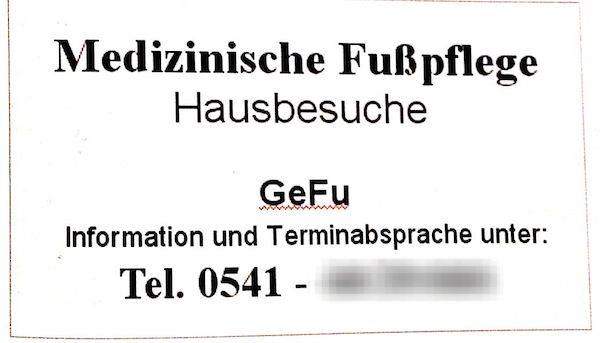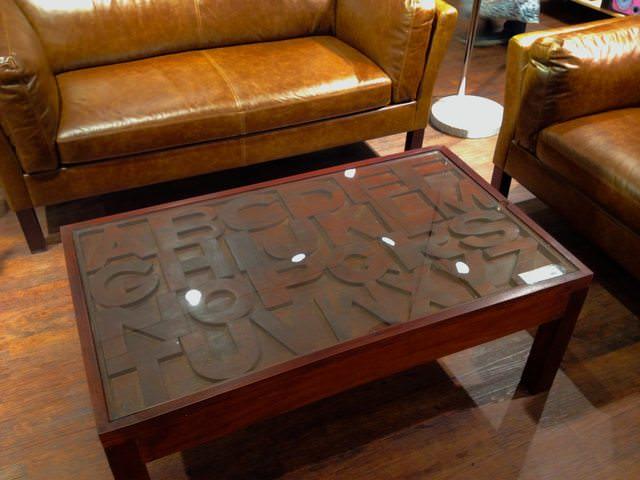
Die Leerzeichen können dann ja die Frauen beisteuern …
Hm. Ich kenne die eine oder andere Frau, die durchaus einen Gedankenstrich beisteuern könnte. :-|
Leerzeichen auch nicht … eher Lehrzeichen  :biglove: .
Ich spendiere eine Locke.  ;-)
Dann kriegen wir zumindest eine Mail-Adresse zusammen ...
Falls noch jemand was für’s Wohnzimmer braucht:
gesehen bei Butlers in Osnabrück
Ist das Bild spiegelverkehrt?  :-|
Das Foto ist nicht gespiegelt. Gespiegelte Buchstaben sehe ich jetzt auch keine, ich finde aber besonders M und W merkwürdig mager ...
War auch nicht ganz ernst gemeint :-) Ich sehe vermeintlich alte Holzlettern, die spiegelverkehrt sein müssten, damit sie im Druck seitenrichtig sind. Und das W sieht mir aus wie ein M, das auf dem Kopf steht.
Export durch Bildschrimfoto inklusive Rechtschreibkorrektur :hammer:
Aus unserem Gemeindeblatt und die Anzeige ist da so nicht das erste Mal drin  :neenee:  (Die Telefonnummer habe ich unkenntlich gemacht …)
Ja, gab ers nicht mal früher solche Massage-Sandalen mit hunderten Gumminoppen? Ich meine, dass mein Vater so etwas meiner Mutter geschenkt hatte, die hatten Holzsohlen und so eine rote Gummi-Noppen-Innensohle, die käme in der Optik dem schon recht nahe.
Ich bin mir jetzt nicht ganz sicher, ob ich dies jetzt unter die typografischen, oder doch besser die orthografischen Fundstücke einsortieren soll, aber ich persöänlich finde es in beiden fällen schlimm, vielleicht hätte es auch noch in die Design-Fundstücke gepasst, denn auch da erkenne ich eigentlich keines in diesem Sendungslogo.
Ich habe hier spontan das in 2 Spalten gelesen: DER LANGE VON / SCHATTEN KULTUR und rätselte über die Schattenkultur.
Offensichtlich ist da bei BR α die Kultur in den Schatten geraten, denn dann erkannte ich, der Titel der Sendung, in der Professoren offensichtlich eine Art Vorlesung im Fernsehen zu Kultur-Themen halten, heißt „Der lange Schatten von Kultur“.
Und ich frage mich jetzt, müsste es nicht heißen: „der lange Schatten DER Kultur“? - schließlich sagt man ja auch nicht „Das schöne Antlitz von Frau“ oder „die schädlichen Folgen von Erderwärmung“
Und das dann von einem Sender, der einen kulturellen und wissenschaftlichen Anspruch hat?